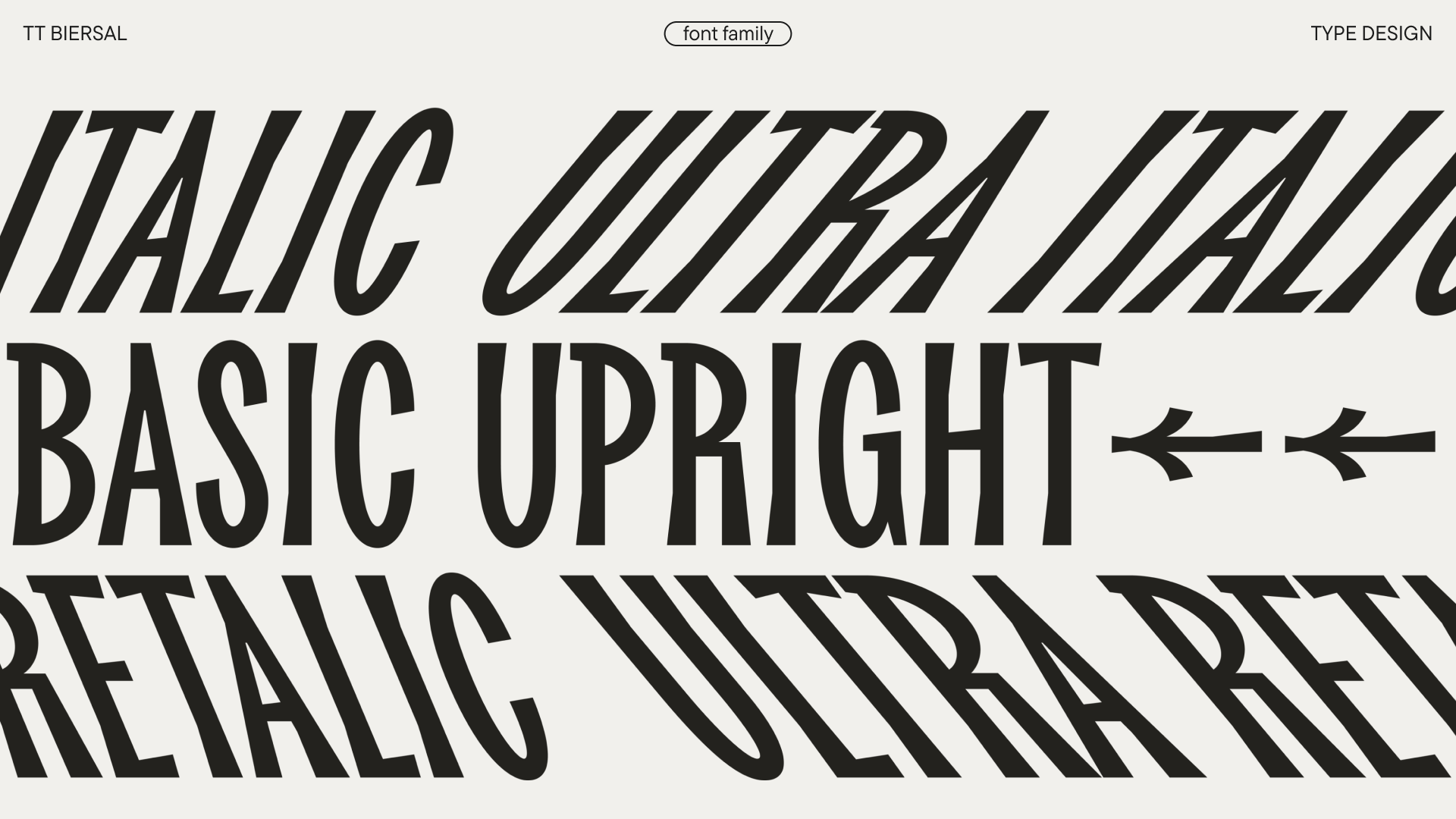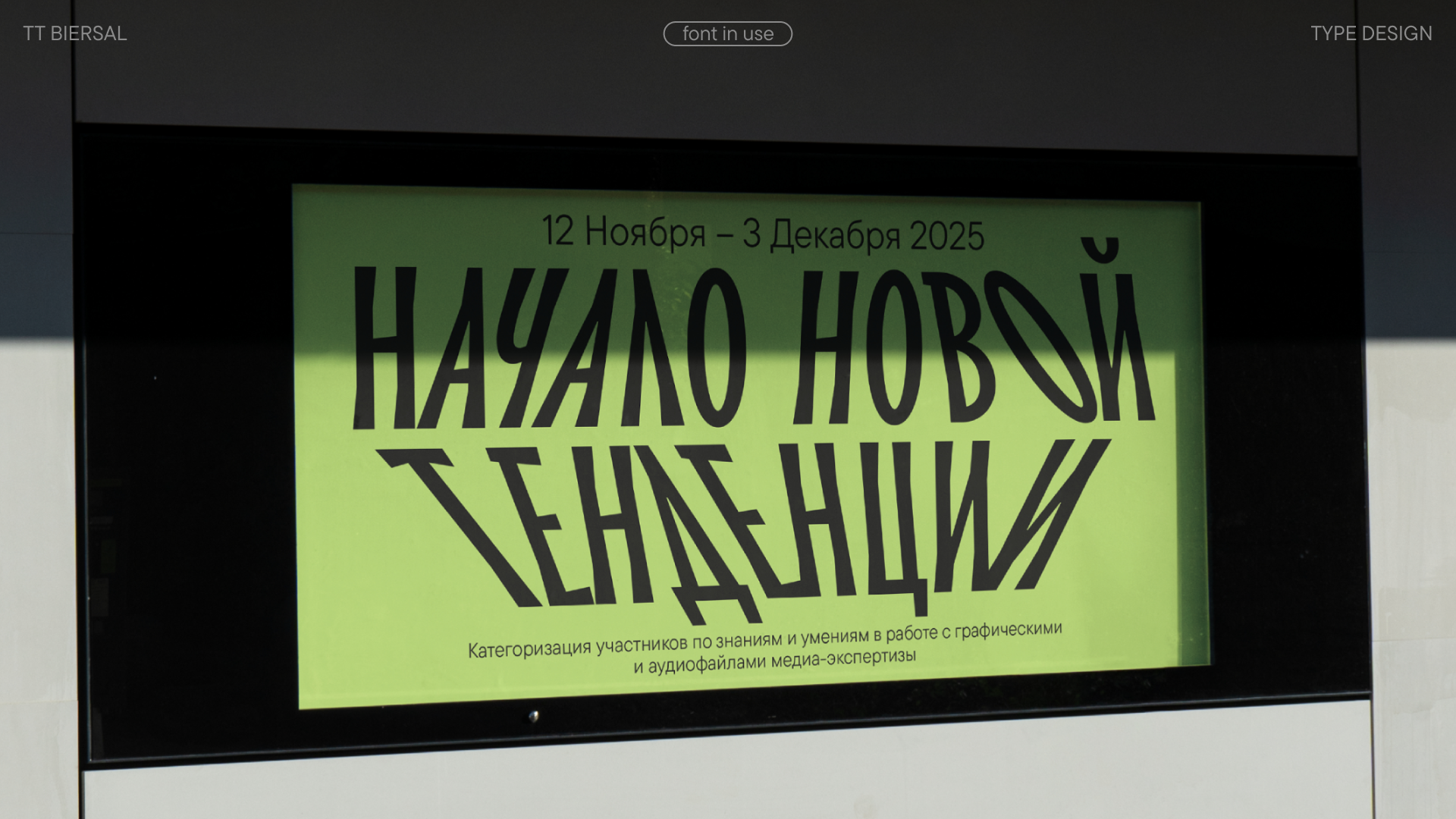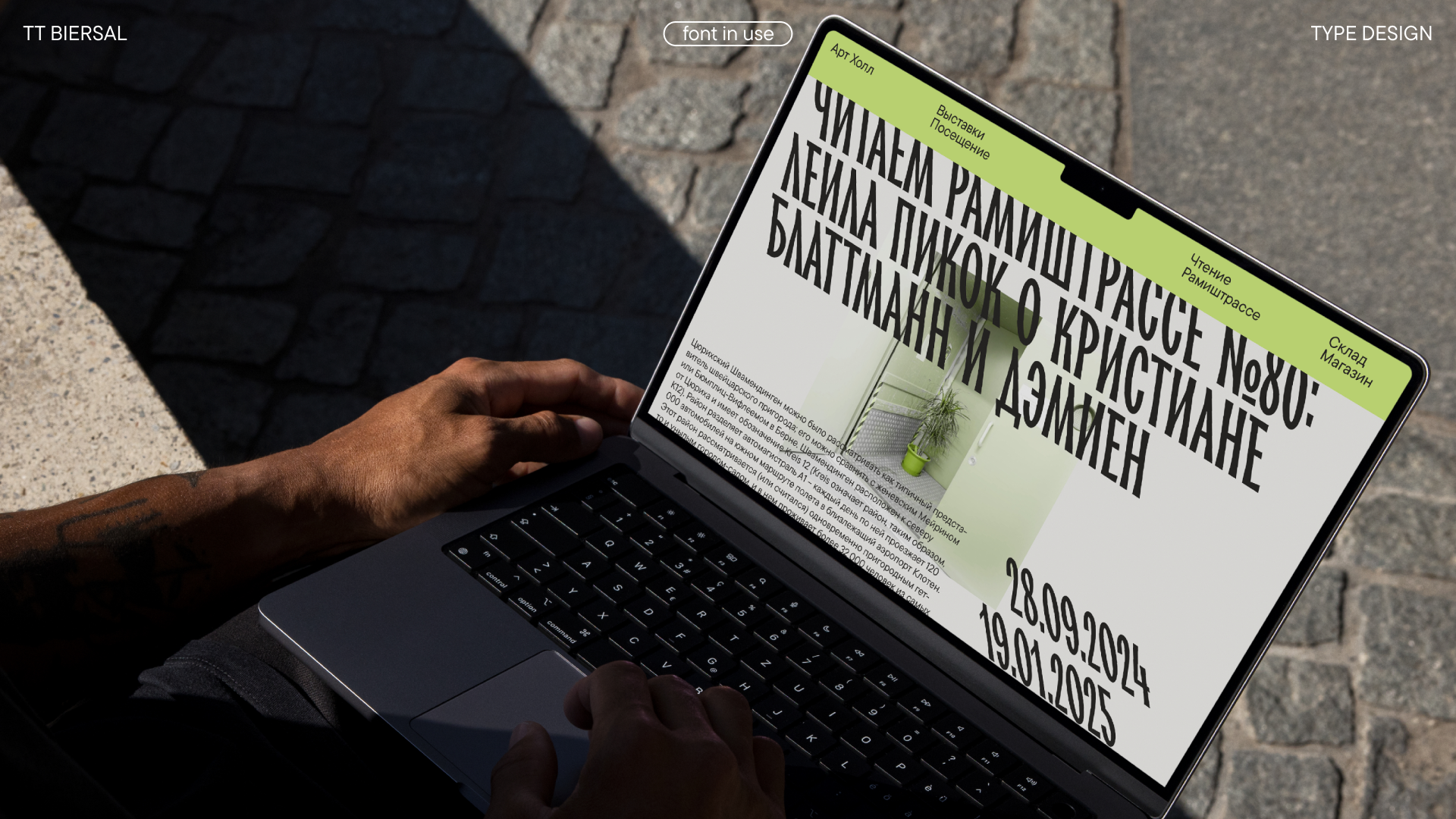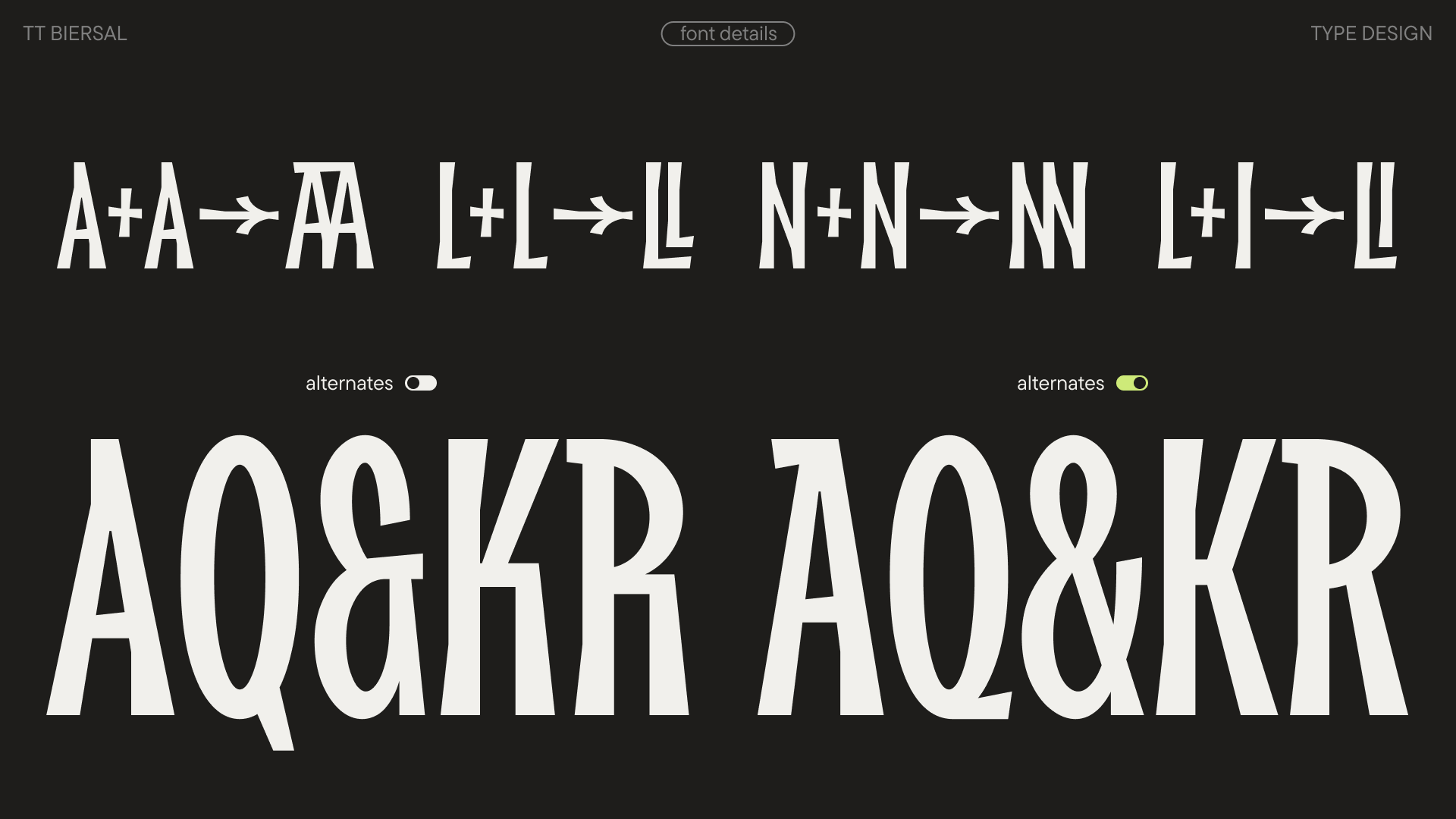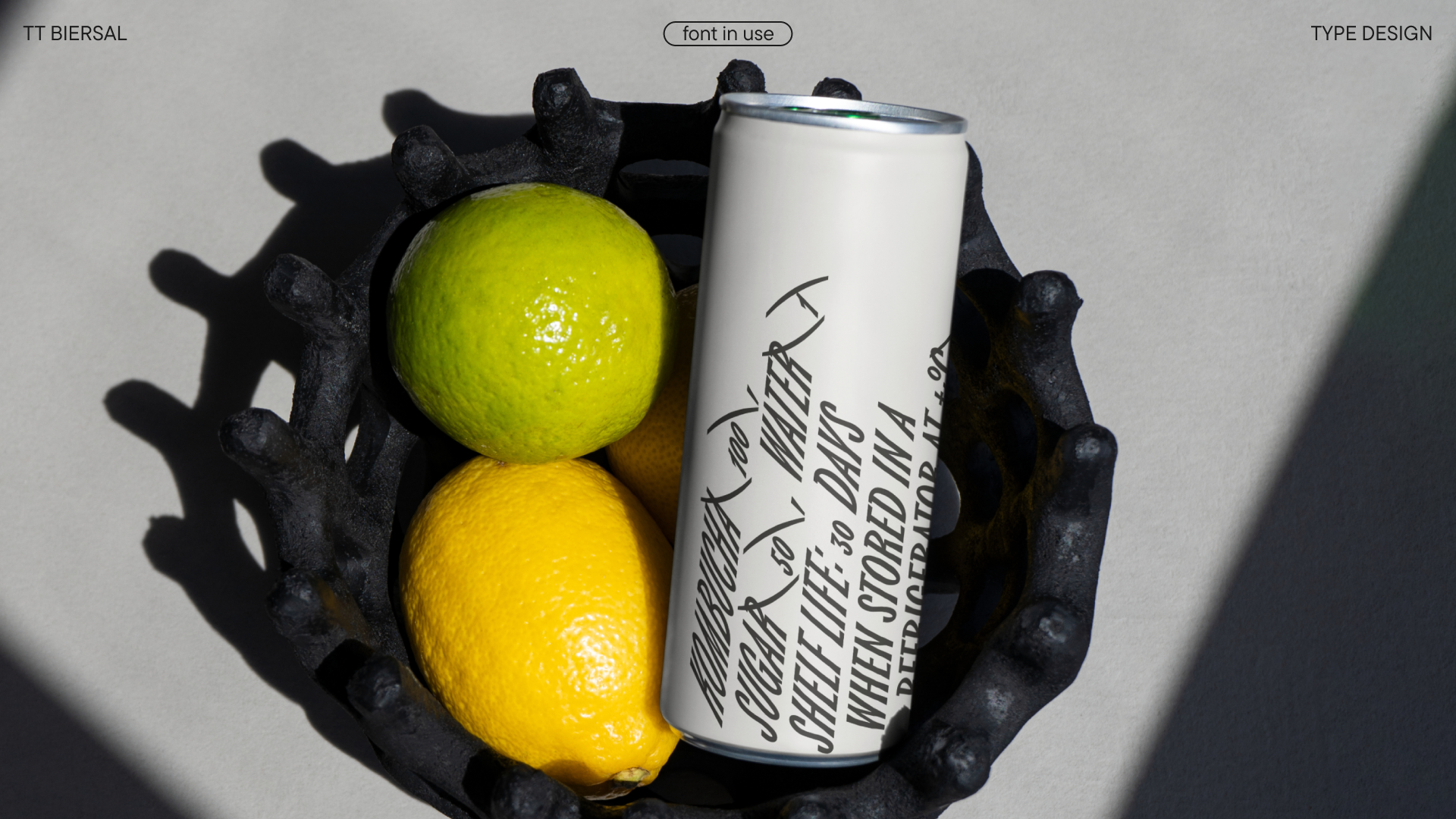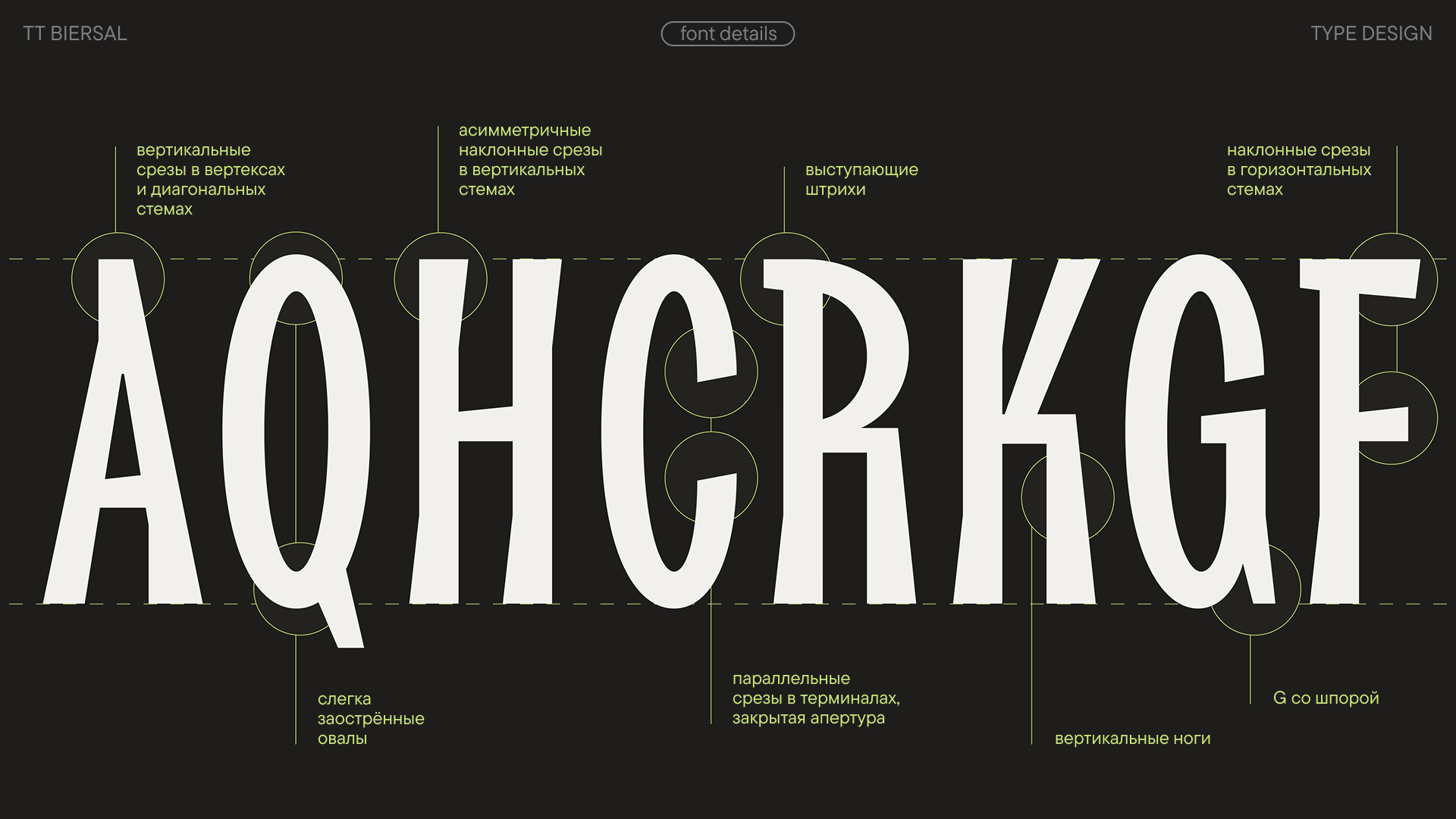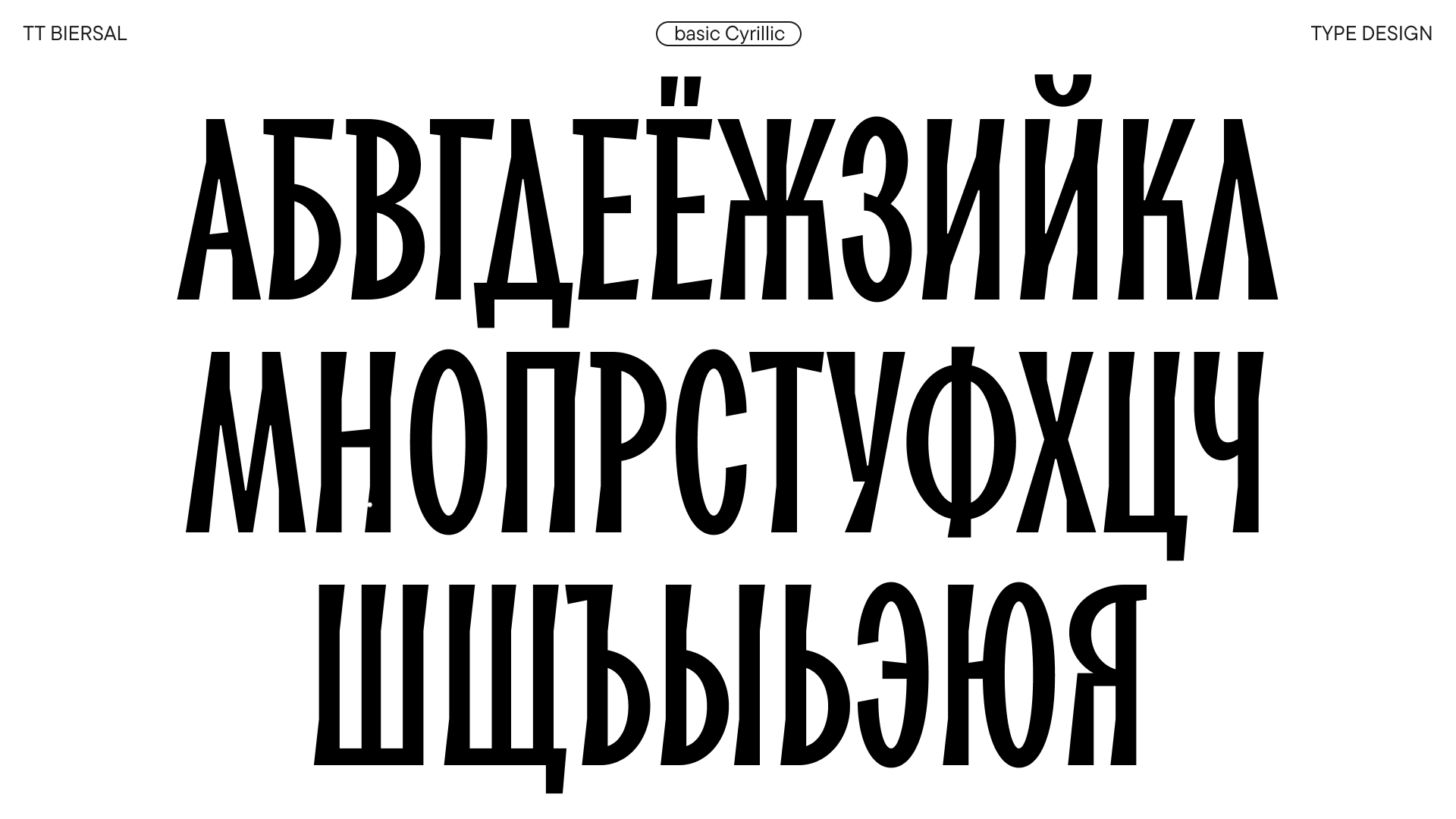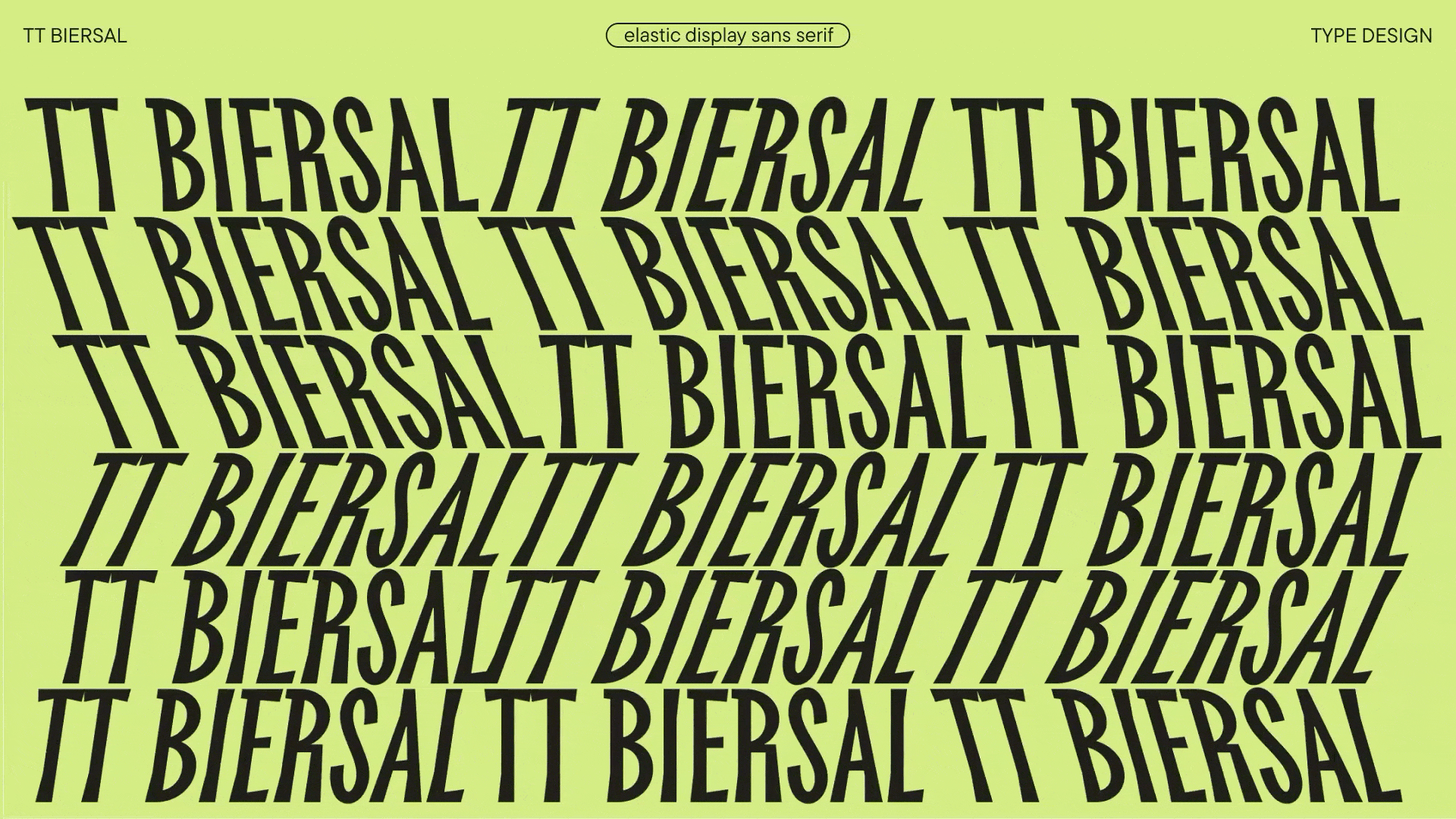
TT Biersal
TT Biersal — это самобытный и энергичный акцидентный гротеск с озорным характером. Отправной точкой для его создания послужил немецкий плакат 1930-х годов. Задача состояла не в буквальном копировании, а в переносе духа живого, неидеального рукотворного леттеринга в современный шрифт.
Рисунок шрифта отличается узкими пропорциями, угловатыми срезами и ассиметричными диагоналями. Ассиметричные срезы под углом в прямых и треугольных знаках создают ощущение рукотворности: будто кто-то собрал буквы из отдельных кусочков. Нестандартные параллельные срезы в терминалах круглых знаков и небольшие выступы в некоторых буквах усиливают эффект и придают шрифту динамики.
Важная характеристика гарнитуры — наличие реталика (шрифта с обратным наклоном). При этом и в италики, и в реталики мы добавили экстремальный наклон — от -40 до +40 градусов. Это открывает безграничные возможности для композиции: комбинируя шрифты с разным наклоном, дизайнер может создавать эффекты движения, объёма и тени.
TT Biersal идеально подходит для проектов, требующих смелого и запоминающегося визуального высказывания: айдентики музыкальных фестивалей, и выставок крафтовых брендов, киноафиш.